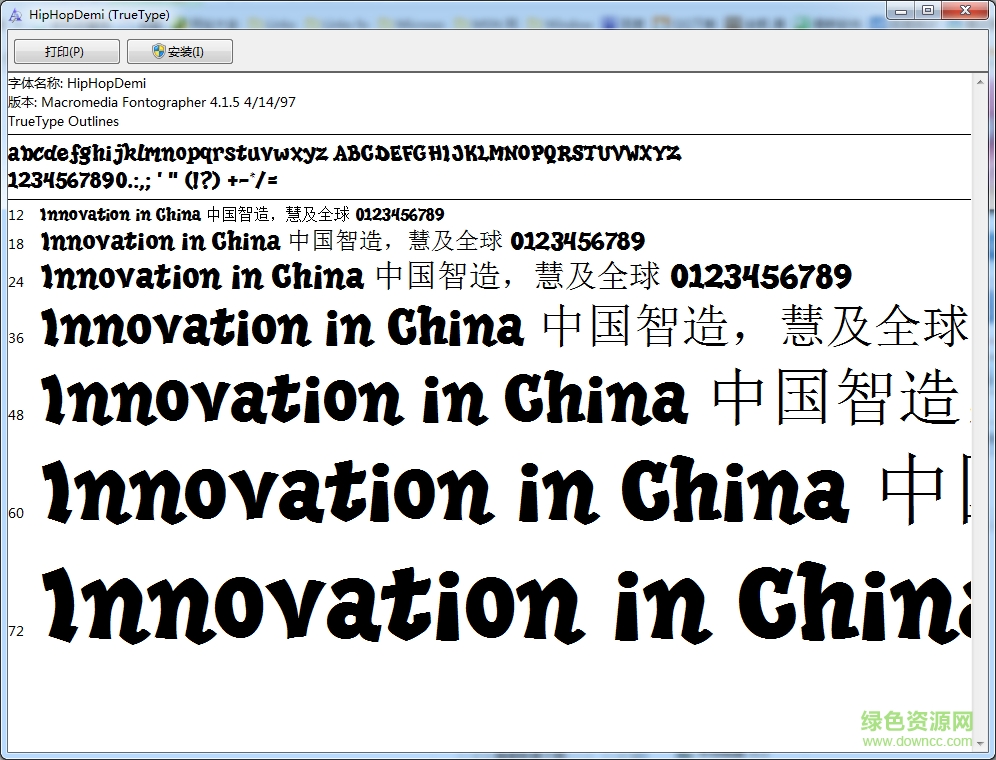
hiphop字體是一款極具嘻哈風(fēng)格的電腦字體,字體時(shí)刻彰顯嘻哈元素,年輕時(shí)尚使用流暢,常用于廣告設(shè)計(jì)、海報(bào)宣傳、圖文印刷等多種領(lǐng)域??靵砭G色資源網(wǎng)下載體驗(yàn)吧!
字體造型規(guī)整,富于力度,給人以簡潔爽朗的現(xiàn)代感,有較強(qiáng)的視覺沖擊力,這種個(gè)性的字體,適合于機(jī)械科技等主題。